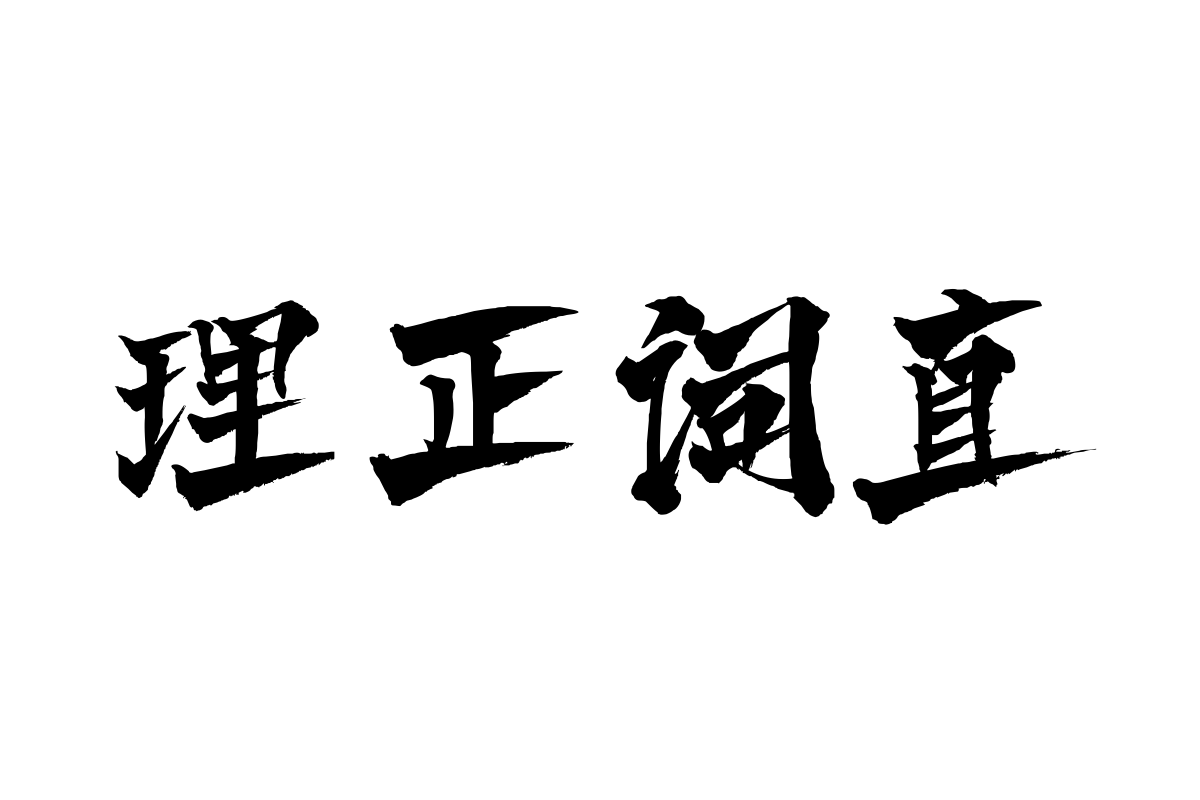
三极虎啸体是一款中文字体,由北京华文字库有限公司开发。这款字体以其独特的设计风格和丰富的笔画变化而受到广泛赞誉。它采用了一种类似于虎啸的形态,通过夸张的笔画和独特的结构,展现了汉字的独特魅力。
三极虎啸体的主要特点如下:
1. 笔画丰富:这款字体的笔画数量较多,每个笔画都有其独特的形状和风格,使得整体字形更加生动有趣。
2. 结构独特:三极虎啸体的字形结构与常规汉字有很大不同,采用了一种类似虎啸的形态,使得整个字体显得更加独特和有个性。
3. 易于识别:尽管三极虎啸体的字形独特,但仍然保持了一定的可读性,使得读者能够轻松识别出其独特的风格。
4. 应用场景广泛:三极虎啸体适用于各种应用场景,包括书籍、海报、包装设计等,能够满足不同用户的需求。
总之,三极虎啸体是一款具有独特风格的中文字体,它的设计和制作都体现了作者对汉字艺术的深厚功底和独特见解。